什么叫文字编排的节奏感?深度干货
我们在做设计的时候总是会听到,要注意“节奏感”。关于节奏感这个词,大多数人似懂非懂,可能明白它是什么意思,但是在设计中都应该注意哪些节奏感,却还没有一个比较清晰的思路。我们都知道音乐是有不同种类的,有古典音乐,有摇滚音乐等,它们之间的不同,很多时候是节奏给我们带来的感受不同。在设计上也是一样的,掌握节奏感就能控制画面的变化和气质的传达。
先理解什么是节奏感。
我们常说的生活节奏,可以理解为,假如你在规定时间里,你只需要上班和回家两点一线的生活。
但是当你有了孩子还要去幼儿园接送,晚上还要去健身等,这样就是生活节奏加快了。
我们常听到的节奏感其实是来源于音乐的。
不同节奏感的音乐会给人不同的感受,就像音乐1这种,会给你一种平静舒缓的感觉。音乐2这种就会有种比较喧闹、比较活泼的感觉。
说到设计的中的节奏感,从绘画里也可以看出,这是吴冠中的绘画作品,看似很简单的画面,但是这种水流的蜿蜒的感觉让这个画面变得灵动起来。
去掉这些流动的线之后,整个画面就变得很平静了。失去了那种蜿蜒流潺的感觉。
在我们很多图像网站里都用了这种瀑布流的方式,不仅是为了方便不同尺寸的图片的载入,在很多时候这种方式,相对于平铺的图片放置会更让人舒服而不枯燥。
在平面设计里,我们在学习平面构成的时候节奏与韵律是常常放在一起说的。
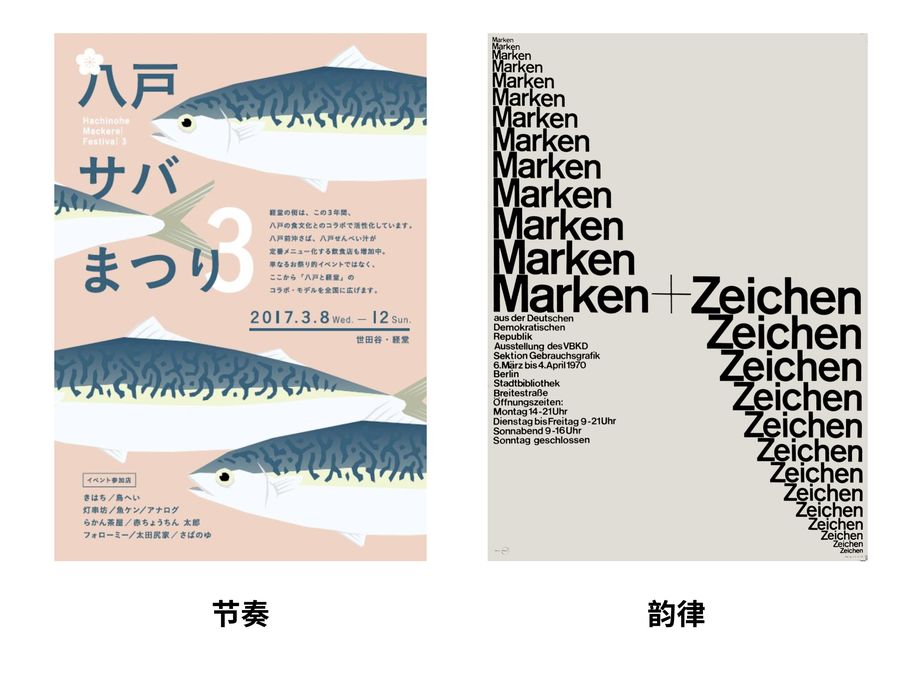
我们可以看海报去理解,第一张海报那几条鱼摆放的位置是没什么规律的,但是它却能形成节奏感。那么在第二张海报,我们能清晰地感受到它的节奏与韵律的变化。所以节奏是有规律或者无规律的变化的,韵律是有规律的变化的。
包括去百度百科查找相关信息也是表达类似这样的意思。
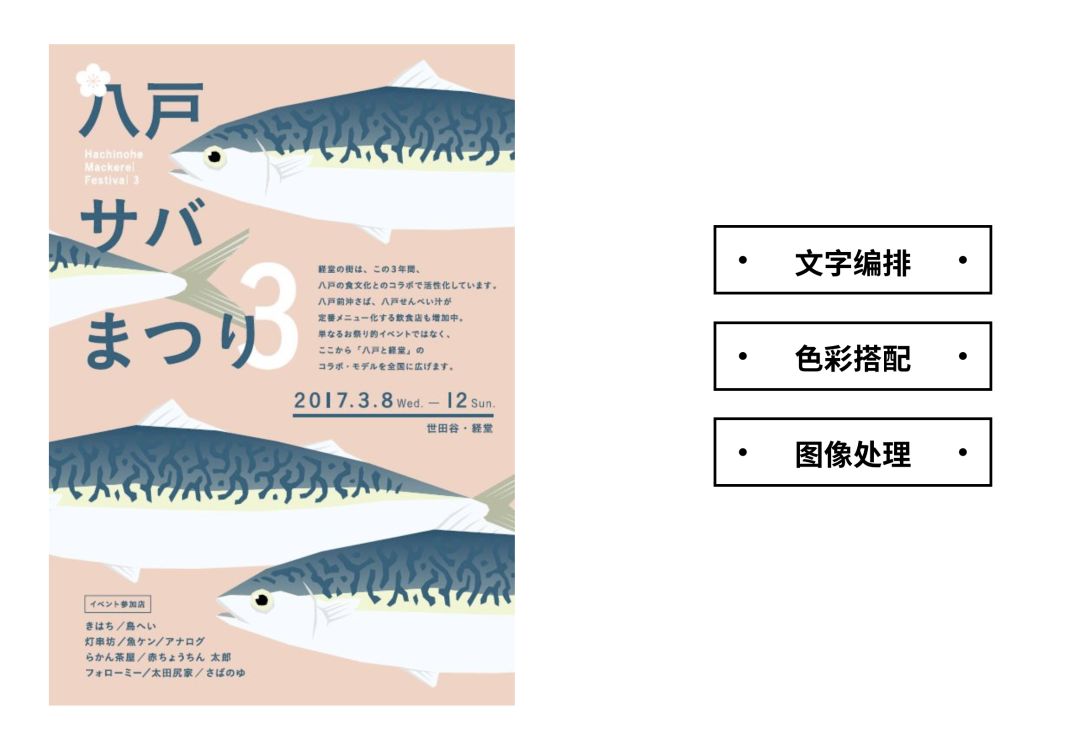
一个版面里的节奏影响是多方向面的,有文字编排、色彩搭配、图像处理等。
今天我们要讲的是文字编排里的节奏感。在文字编排上我们为什么掌握节奏感呢?
我们在看一些纯文字的书籍的时候,很容易犯困。
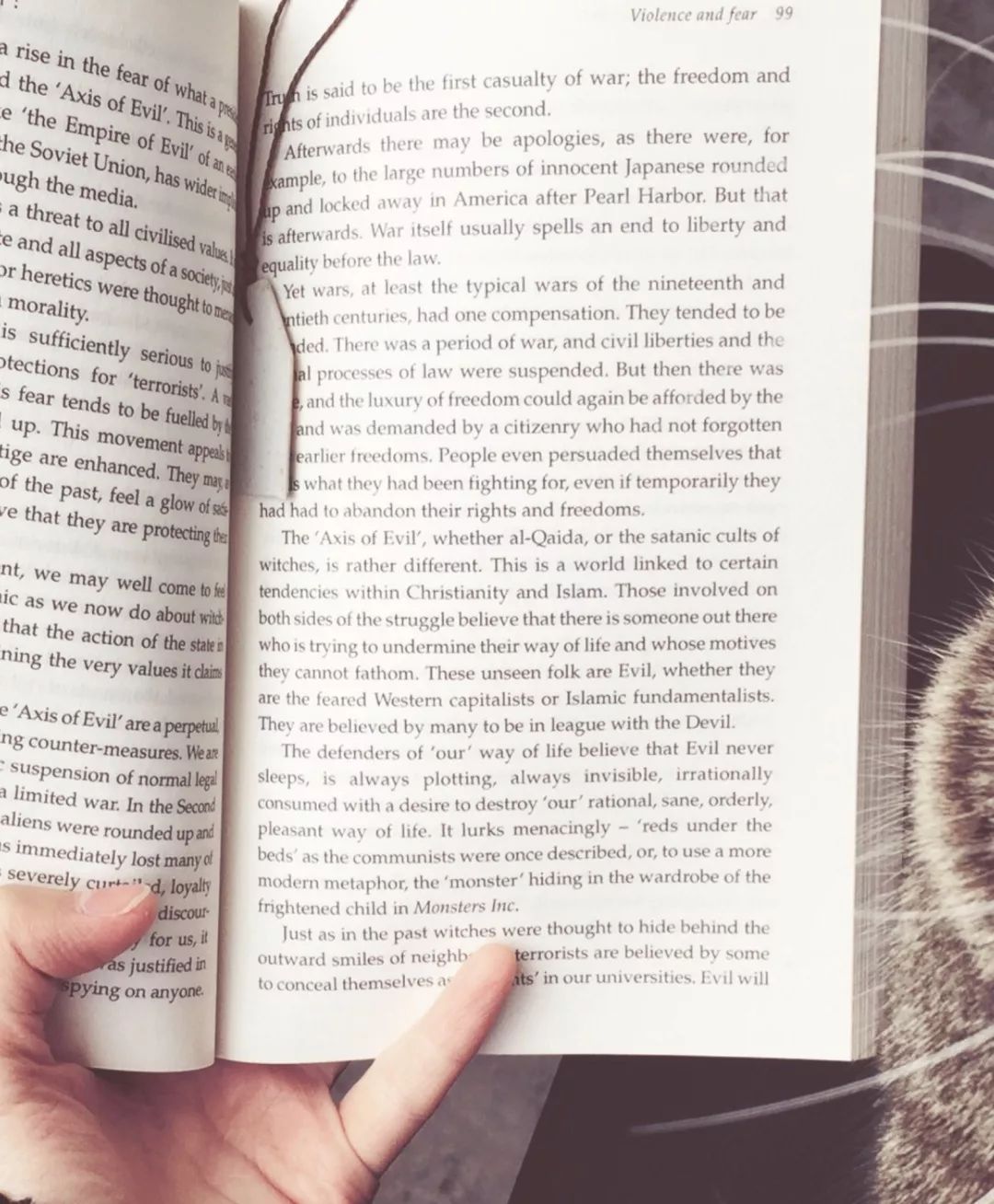
这就是因为书籍的文字编排几乎没有节奏感,所以相对来说是很枯燥的。
有一些不同的书籍设计或者杂志会在里面加入了图片、对文字与板式进行处理,使它们变得有变化性,就会调节这种节奏感。让画面阅读不再枯燥。当然了,画面左边是因为大量的信息的传达不适合做过多的变化,否则阅读过程会有阻碍。这也是根据不同种类的信息从而把握不同节奏感的结果。
所以在这个画面里标题是节奏感比较强的,在保证阅读性的同时也做到了装饰性。那么由于下方信息量比较多,这些文字又需要被快速传达,所以这些文字的编排就会趋向于阅读性。
掌握文字编排的节奏感对画面传达的气质的影响是非常大的。就像这两张海报,它们的背景图片气质是很像的,都是天空的大留白,但是,完全不同的文字编排,就让第一张海报表现出活泼可爱的感觉,第二张海报表现出平静安静的感觉。
我们可以理解为,随着几乎没有节奏感到节奏感比较弱再到节奏感强,它的画面是可以呈现出由静止到舒缓再到动感的。
在文字编排中有非常多的对比,是一个非常大的系统,今天我们主要去梳理一下文字编排时的一些影响因素,以及在文字编排上一些需要注意的细节。(我们今天会讲这些影响我们文字编排的节奏感,字体种类、大小、长短、位置、疏密、颜色、组合形状和方向。)
文字种类就是我们对文字的类别进行分类,在字体种类里一般分成了衬线体与非衬线体,但是在中文里,我觉得主要由这五大类组成,分别是黑体,宋体,楷体,圆体与书法体。
包括字体家族里的不同字重。
不仅是这样,对于同一个字体我们还分常规体、窄体、扁体。
一段文字只选择上面的所说的变化就已经可以有很多种了。我拿了一段数学公式装❌。这里我们算出有105种。所以文字编排时稍微不注意就会有太多的变化性。
更何况我们经常在版面里加入其他国家语言的文字,这些都会影响文字的节奏感。
所以我们要学会控制这种节奏感,一般来说我们日常比较常用的就是黑体配无衬线体,宋体配衬线体。并且在字重上我们都要注意协调。尽量使它们看一起是一样的粗细度。
不同的字体搭配起来是有一定难度的。这种节奏感就好像不同风格的音乐的结合,它们之间的衔接与融合会比单纯的某一种风格的音乐制作起来更难。
这种不同类型的文字的搭配,对于排版和运用的能力有一定要求,运用不好就会传达不了精准的气质与信息的传达。在电商里的反例是比较多的。在我看到的这张图里,它同时用了无衬线体与衬线体的结合,画面没有清晰呈现出准确的气质。大家可能会说它是简约高贵风,但是这是一个大范围,在简约高贵里有现代的高贵,有复古的高贵,还有一些与众不同的高贵等。
我们尝试把左边的衬线体换成无衬线看看。是不是有种现代都市的气质?
如果都统一成衬线的话,是不是一种精致的时尚感就出来了呢。统一这种文字的种类能更加精准地传达画面的气质。
刚刚我们也说到字体的混搭会产生混乱和怪异感,要慎用,但是如果我们的画画就需要这种感觉呢,当然就可以用这种特性来故意营造一种怪异感,当画面的字体种类越多的时候,所营造出来的节奏感会更强烈。
我们看这个画面也是这样的,周围的很多图形和各种各种样的字体类型让这个画面变得搞怪活泼。
就算去掉了周围的图形,文字这传达出来的搞怪感觉也依然存在。
接下来我们用这个文案来做一个案例演示下,由于平时很多都是用同一种类型字体搭配,那么这一次就挑战一下,我就打算做一稿用不同类型字体的版面。看看会有什么样的效果。
首先我在版面中划分版块,填上相应的文字,在这里可以看到,我同时用了衬线与无衬线的字体,还用了具有手写性质的字体。不仅如此, 所有的文字我都用了窄体而不是常见的常规体来增强这种怪异的节奏感。
最后加上一些图形处理一下负空间,这个案例就完成了。
为了减少影响,我把图片遮住单看文字组,我把这些字体都变成黑体了,对比可以发现,还是原来的文字组更有搞怪奇异的节奏感。右边这个因为板式与图形的完整性使得它看起来并没有很大的问题,但是它的确是缺少了像左边这种古典与现代结合的节奏感。
文字的大小节奏可能会有人理解为这样,但是我们一般不会这么做。
我们更多地是用在标题与内文的对比。
节奏变化比较大的文字组会给人一种冲击力,让人无法忽视标题的存在,就好像我在大声告诉你一句话的感觉,会比较强硬与喧闹。
节奏比较平缓的文字组表现出一种精致、安静的感觉。
我们把它们放到画面里看下,这个标题与内文的对比很大,并且在这个版面中占据一定的大小,这种时候有没有觉得这个画面呈现出一种,好像在播放新闻的感觉,好像在说这个小岛有什么重大新闻一样。
但是当标题变小时,整个画面呈现出比较平缓的节奏感,很符合画面传达出来的安静舒缓的感觉。
这种方式很多作品都有,这种标题和内文的对比,或者说是文字在版面的占比比较大时,就可以体现出这种很强烈的节奏,让人很难忽视这些文字内容。同时画面也更容易传达出一种力量感。
往往想要营造这种安静感的时候,比较注重画面整体的感觉,就不需要太多的文字变化,甚至为了区别文字层级而需要有的文字大小,也尽量地在减少对比。
我们都知道音频都是这种长短不一的声波图,因为这种长短不一的变化感受会给人带来节奏感。
所以也有以这种形式来编排文字,表现节奏感的系列广告作品。
它比较经常出现在居中对齐的文字组上。
但是我们要注意的是,你会发现很少情况在两个极端之间直接过度,比如说一长一短。
在没有文字大小的对比情况下,如果文字的长短对比太小,我们先不说节奏感,我们可能会有种疑问,它到底是想两端对齐还是居中对齐的呢?所以这种两端模棱两可的情况最好避免。不能模棱两可,对比太大又会不够美观,所以我们去创造节奏感的时候要注意这些问题。
毕竟它不是让人阅读时间很长的文字,所以我们就需要调节这种节奏让它看起来美观而且不枯燥。
这是我随便在购物网站截图的,你会发现它们的文字编排都很注意我刚刚说的短长短的节奏感。
我找了两张都是黑色背景并且配图比例也差不多的海报作对比说明这个问题。
因为图像的干扰我就同时去掉了图片,还有也把右边红色的字变成了白色,它们之间的对比变得清晰了,左边的文字规划在版面中显得更有活力,右边版面的文字集中在一块,就像我们前面提到的小说书籍内页一样。这样的文字编排在阅读上会比左边的缺少节奏感。但是我在这里要说的一点是,左边海报本身的图像没有右边的有冲击力与活力,所以我们如果要真正做对比的话。
用左边的图像放置在两个不同的版面来作对比,这样大家应该能感觉到差别。左边的版面虽然没有表现特别强的节奏感觉,但是至少版面不是特别压抑的。至于右边的我们会觉得很沉静,配合这种黑色的背景比左边更压抑。这就是文字编排在版面的影响。
不仅是文字组之间,标题的有意放置不同的位置就可以营造这种节奏感,是因为它依然可以使得我们的阅读视线发生变化。
比较随意编排的文字组也会比,比较拘谨正式的文字组看起来更有节奏。更活泼。
接下来我们用案例来演示。
首先选择纤细的宋体会比较符合这个画面的气质,很多人可能把文字组放在画面四个角就算大功告成了,但是这个画面既没有一个亮点吸引我们,而且画面里的元素都非常得散,没有体现出一点活泼的味道。
这个时候我们可以效仿刚刚我们看到的标题的做法,拉开距离,调整位置让它有上下浮动的节奏感,包括文字上我都做了一些切割移动让它们活泼,再加上线条让它们更有联系感。这个画面就会比刚刚活泼多了。
案例完成。
左边紧凑的文字字距会呈现出一种张力,一种急促的节奏,营造一种紧张感。右边宽松的字距画面会更缓和,不同的字距在版面中有宽松对比,也营造出了一种节奏对比。不会感到枯燥。
很多人可能没太去注意这些文字编排的小细节,这两版里哪一个更符合平缓的节奏感呢?答案是下面这个。第一张这样做也没错的,但是我们想让文字也能相应地呈现出一种透气感的话,第二张的会更加符合。
颜色的问题大家应该了解了很多了,这里就简单提一下,就像我们在营造一种氛围的时候选择的气球颜色都是非常重要的,我们选择饱和度比较高,颜色种类比较多的气球的时候,是想营造一种热闹活泼的感觉的。但是如果想营造一种浪漫安静的氛围时就用了很多白色或者淡色调的颜色。
就像这个banner一样,中间不同颜色的文字为这个画面增加了很强的节奏感。变得很活泼。
很多时候我们不需要太强的节奏感,所以我们经常给文字做一点的颜色变化,来让画面更鲜活。就像这个banner,如果它没有了左边那个粉色的颜色的跳跃。
这个画面就会变得很沉静。
如果,画面文字的粉色变多,它的节奏感觉变得更强。
不仅是因为这个颜色本身的跳跃性比较高,而且也是因为颜色的不停切换导致这种节奏感的增强。所以不同颜色的占比也是需要考虑的。在这里主要是因为模特身上没有玫红色,所以左边不适合用过多的玫红色,用全黑都会显得很沉闷,所以这里选择用一次玫红色让这个画面鲜活。
由于我们要压住图片的节奏感,不让它太乱,所以我在周围的空间编排文字是呈现一个既有文字层级关系,但是整体是呈现矩形的文字组。现在这个画面看起来的确不会乱,但是文字还是少了和图片活泼气质契合的节奏感。
分析一下这个画面,是宇宙系列的感觉,所以我就加入了环形的文字,然后再加一点与图片呼应的颜色。这个画面就会比之前更和谐。在做的过程通过减少变化与增加变化让画面逐渐接近自己的预期。
总结一下今天我们讲的,我们今天讲的是文字编排中的节奏感,在一开始,我分别给大家讲了从生活节奏、音乐节奏、再到设计的节奏去理解什么是节奏感,然后我还讲了关于文字节奏感对于画面的重要性,无论是对信息的传达还是对气质的表现,它的影响是非常大的。最主要的部分,我讲了影响文字编排的节奏都有哪些因素,比如文字类型、大小、方向、长短、文字组合形态等。把握自己要传达的节奏,才能正确传达信息。大家也可以用这种方式去看作品,分析它的节奏感是通过什么方式形成的。久而久之,对节奏感的掌握就会更加熟练与精准。今天的教程到这里就结束了,感谢大家的收看,我是大希,下期再见。